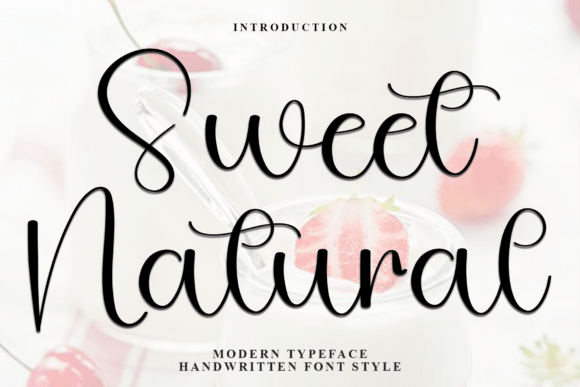
Sweet Natural
Wenn Sie nach hochwertigen Assets wie Sweet Natural suchen, ist dieses Premium-Paket eine fantastische Wahl für Ihre kreativen Projekte.
Egal, ob Sie POD-Produkte (Print on Demand), Hochzeitseinladungen oder Social-Media-Grafiken erstellen, Sweet Natural ist die ideale Wahl.